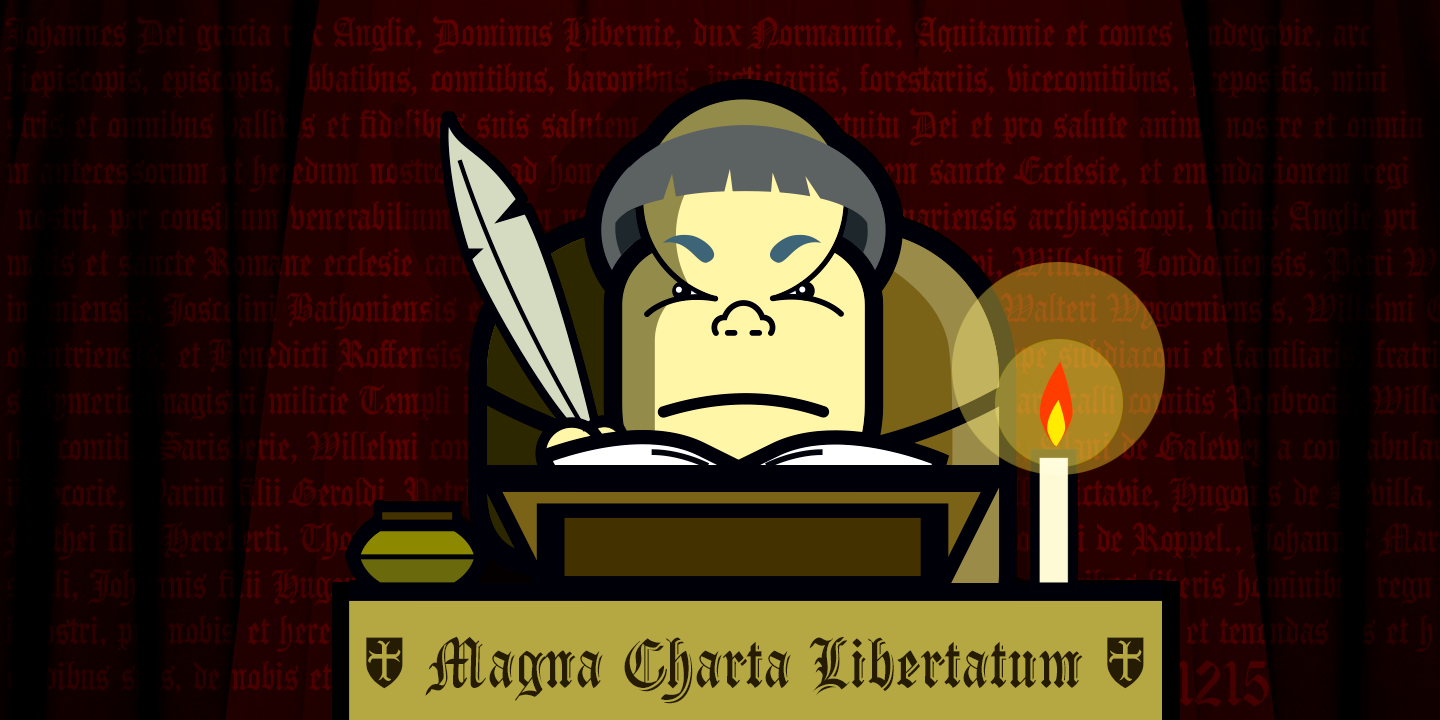
Carta Magna Font
A Carta Magna Font é uma elegante escolha para designers que buscam adicionar um toque clássico ao seu design gráfico. Inspirada no Gothic estilo, esta fonte calligráfica medieval se inspira na história do primeiro precursor das constituições políticas modernas. Ideal para criações de caráter formais e históricos, sua elegância e delicadeza a tornam uma opção popular para editoriais, selos e materiais educativos. Com seu designer defharo, essa fonte Gothic oferece um estilo arcaico e sofisticado que combina perfeitamente com projetos de letras grandes. Seja para criar rótulos elegantes ou documentos históricos respeitados, a Carta Magna Font é uma excelente escolha. Sua versatilidade em diferentes tamanhos e estilos torna-a uma fonte indispensável para designers gráficos buscando um toque de elegância e sofisticação nas criações.